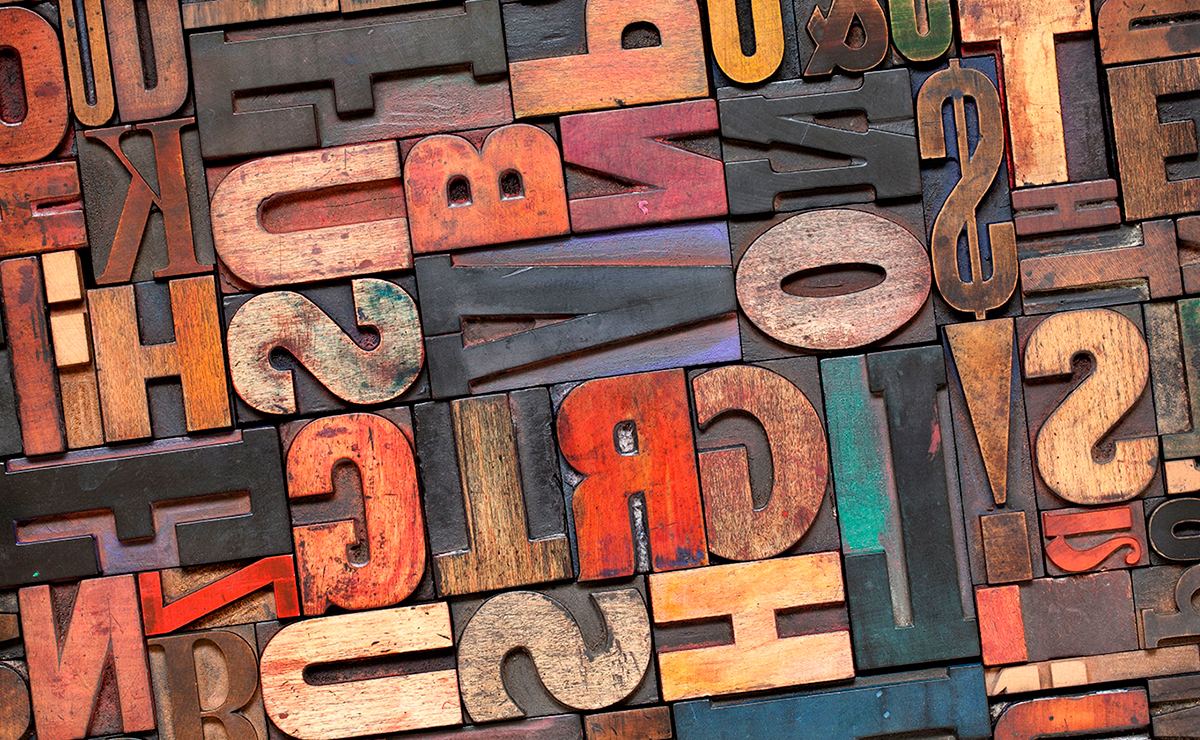
Como todo grupo profesional, los tipógrafos y apasionados de las letras tenemos nuestro propio argot. La terminología es muy amplia y diversa y, no es nuestra intención haceros partícipes de todo nuestro arduo léxico, pero si mencionaros algunas curiosidades.
Para empezar, decir que en tipografía un glifo es la representación gráfica de una letra (ya sea letra, número o símbolo). Aunque en realidad, para el resto de los mortales, un glifo es un símbolo que representa un concepto dentro de la escritura maya. Mientras tanto, un dígrafo es un grupo de dos letras que representan un solo sonido, en el castellano tenemos claros ejemplos de esto con la “qu”, la “ch” o la “gu”.
Para la visualización de una fuente tipográfica, el recurso más utilizado es el pangrama o también llamada frase holoalfabética. Se trata de un texto que emplea todas las letras posibles del alfabeto de una lengua. Es todo un reto intentar componer uno con el mínimo de caracteres posibles y, sea como fuere, su resultado siempre tiene un toque cómico, curioso o al menos excéntrico.
En la clasificación tipográfica, hay un grupo de letras llamadas slab serif o egipcias que tienen los remates rectos del mismo grosor. Este nombre se debe sencillamente a que estas tipo de letras se pusieron de moda cuándo la cultura egipcia estaba en auge.
Entre gente más afín a la tipografía en vez de referirse a mayúsculas y minúsculas, algunos prefieren hablar de caja alta y caja baja. Se las denomina así por el lugar en el que antiguamente se guardaban los tipos de plomo, las mayúsculas iban en los cajones superiores y las minúsculas en los inferiores.
Los números normalmente nos los encontramos con la misma altura, a esto se le llama cifras alineadas, cifras capitales o cifras modernas. Aunque en ocasiones, te habrás encontrado un conjunto de números que varían su altura existiendo cifras ascendientes y descendientes. Estas son las cifras de estilo antiguo, también llamadas cifras elzevirianas, cifras de texto o cifras no alineadas.
La letra “ñ” es original de nuestra lengua. Sin embargo, pocos saben cómo se denomina a su tupé, su sombrero o, como otros dicen, su bigote. A esta parte de la letra recibe el nombre virgulilla. Este término también sirve para referirse a la colita de la cedilla.
En cuanto a la terminología sobre las partes de la letra existen multitud de términos aunque, como bien comenta Enric Jardí en su curso de Domestika, realmente no son muy utilizados en el día a día de los tipógrafos y diseñadores puesto que al final se acaban refiriendo a estos términos como la colita de la “a” o la bolita de la “c”.
Vamos, que en nuestro gremio tenemos una amplia terminología pero al fin y al cabo, en nuestra vida cotidiana, hablamos para entendernos con nuestros clientes y amigos, haciendo determinadas alusiones o inventándonos las expresiones que haga falta. Porque a fin de cuentas, ¡hablando se entiende la gente!